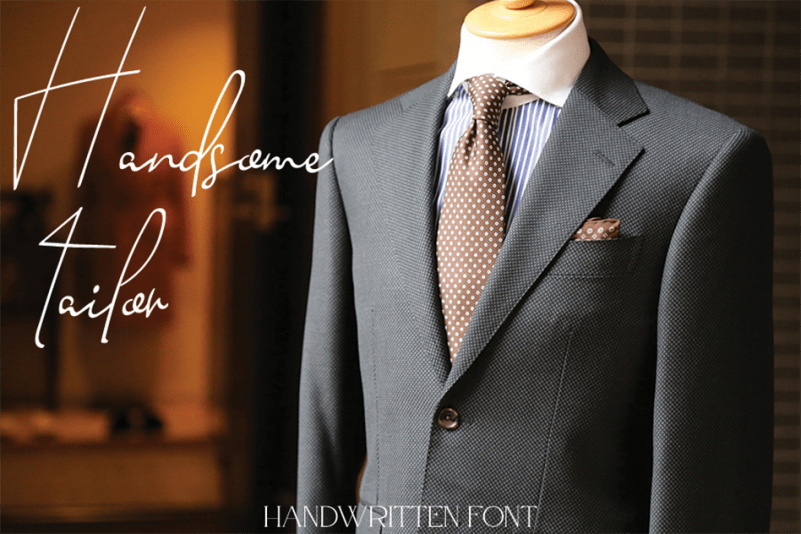
Handsome Tailor Handwritten Font – Fonte Grátis
Handsome Tailor Handwritten Font
A fonte “Handsome Tailor Handwritten Font” é uma escolha perfeita para quem busca um toque delicado e suave no design dos seus projetos digitais, seja ele digital ou impresso. Escreva seu próximo projeto com elegância e personalidade, graças ao cuidadosamente elaborado estilo script que a caracteriza. Esta fonte não é apenas uma opção de adicionar diversão aos teus projetos, mas também um complemento versátil e detalhadamente construído para te auxiliar a tornar tua marca única e memorable. Este é o tipo de font que permite ao designer criar algo muito mais do que apenas texto digital; é um elemento capaz de transformar qualquer criação em uma arte atraente, tornando-a perfeitamente adaptável para uma ampla gama de aplicações. Com “Handsome Tailor Handwritten Font”, você tem à mão o poder de personalizar e encantar seu público com um toque único, criado pelo talentoso designer Erik Studio.